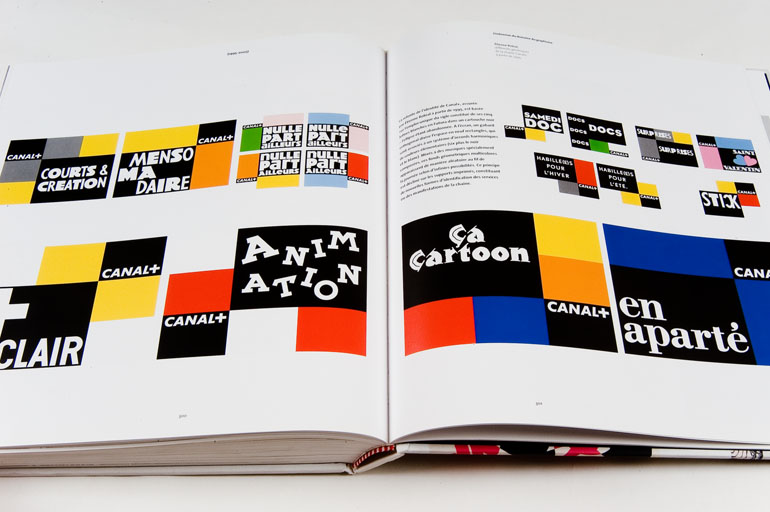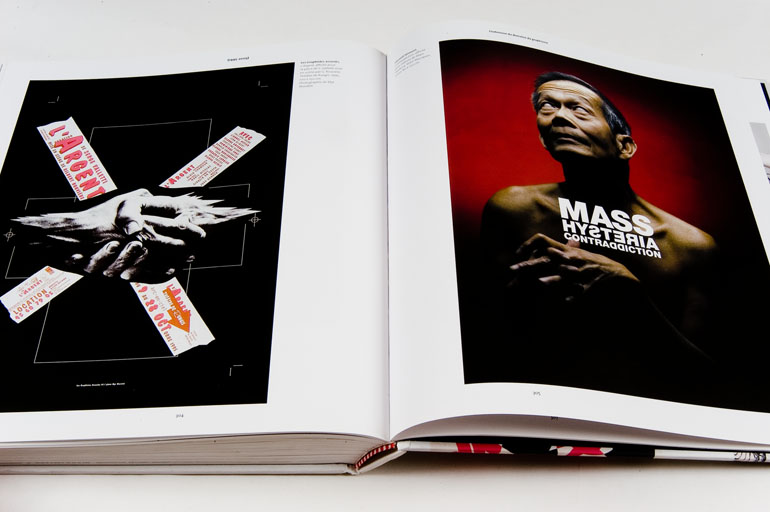
Extention du domaine du graphisme, par Michel Wlassikoff | c’est mercredi 19 mars à 18h30
Les années 1960-1980,
ou la conception
d’un nouvel environnement
écouter, poser des questions
et rencontrer Michel Wlassikoff qui nous conte
l’«Histoire du graphisme en France»
au Musée des Arts décoratifs:
Les années 1960-1980,
ou la conception
d’un nouvel environnement 5/6
Michel Wlassikoff, historien du graphisme, auteur d’Histoire du graphisme en France, une coédition Carré – Les Arts Décoratifs publiée en 2005 décrit et définit les différents aspects de la pratique du graphisme : art de l’affiche, création typographique, graphisme éditorial, de presse, d’information, multimédia, habillage télévisuel. Les évolutions graphiques et typographiques sont examinées en lien avec les grands courants esthétiques français et internationaux, avec les arts plastiques, la photographie, le design ou encore l’urbanisme. L’apport des créateurs et des mouvements graphiques étrangers est précisément indiqué. Ces conférences richement illustrées s’adressent aux étudiants et aux amateurs.